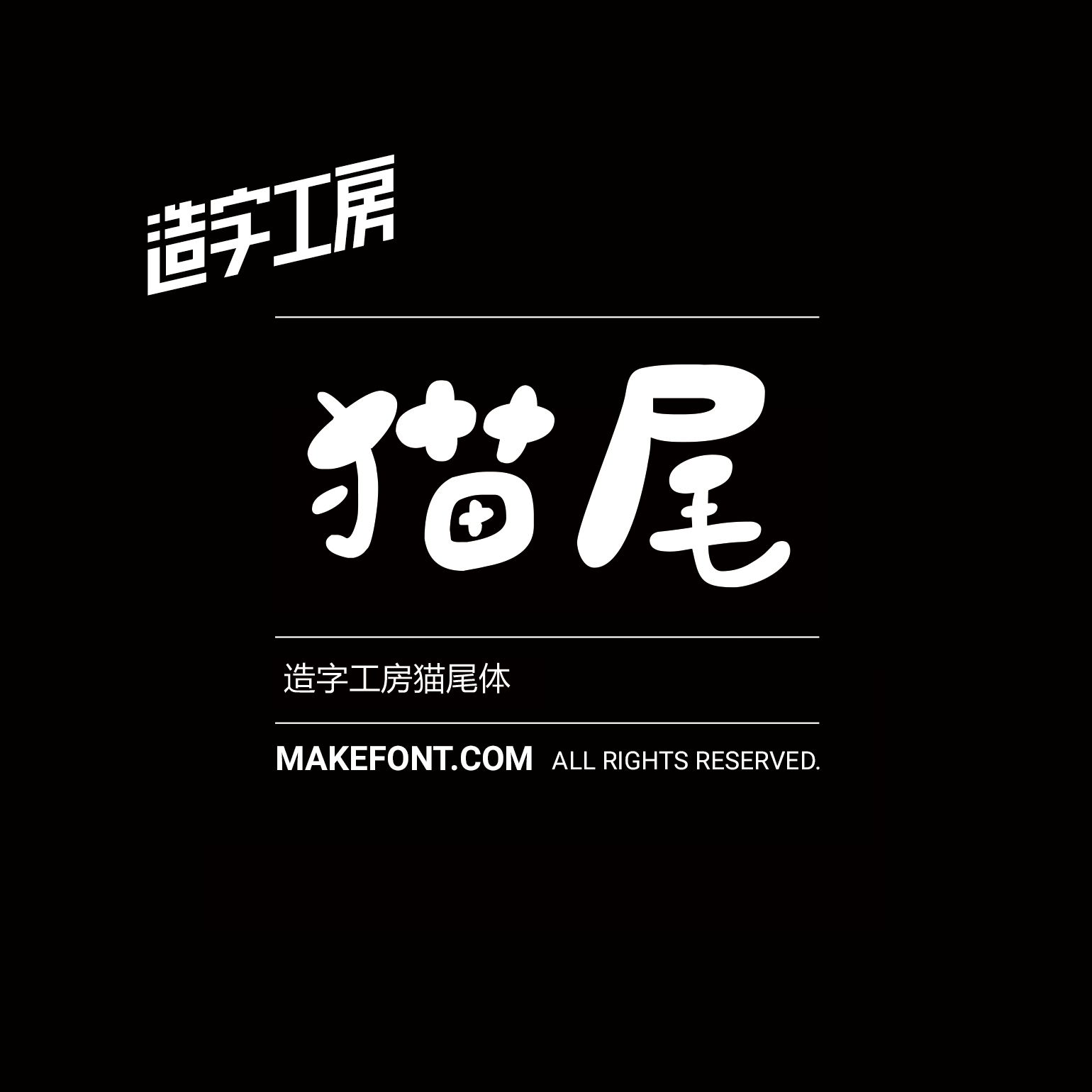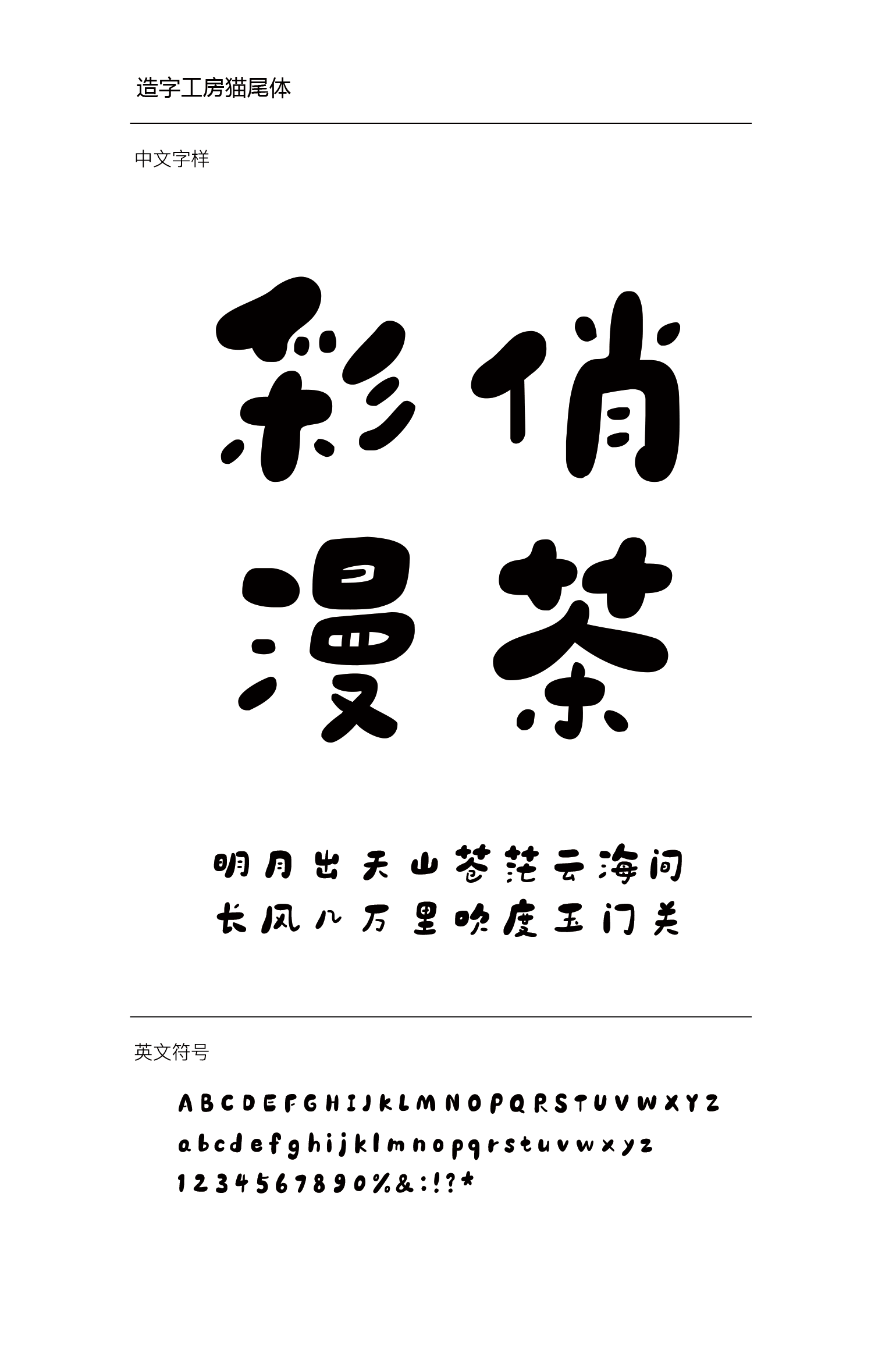
造字工房猫尾体设计说明
造字工房猫尾体,字形灵动卷曲,笔画如猫尾般柔软而富有弹性,风格充满童趣与萌感,结构强化了字体的治愈与活泼,是一款适配文创产品、风格吸睛的字体。本字体为简体字库,采用OpenType/CID格式,Adobe-GB1-5编码。基于中华人民共和国GB2312-80字符集标准,另按需添加101个汉字。共收容字数6864CJK汉字,ASCII常用字符100个。